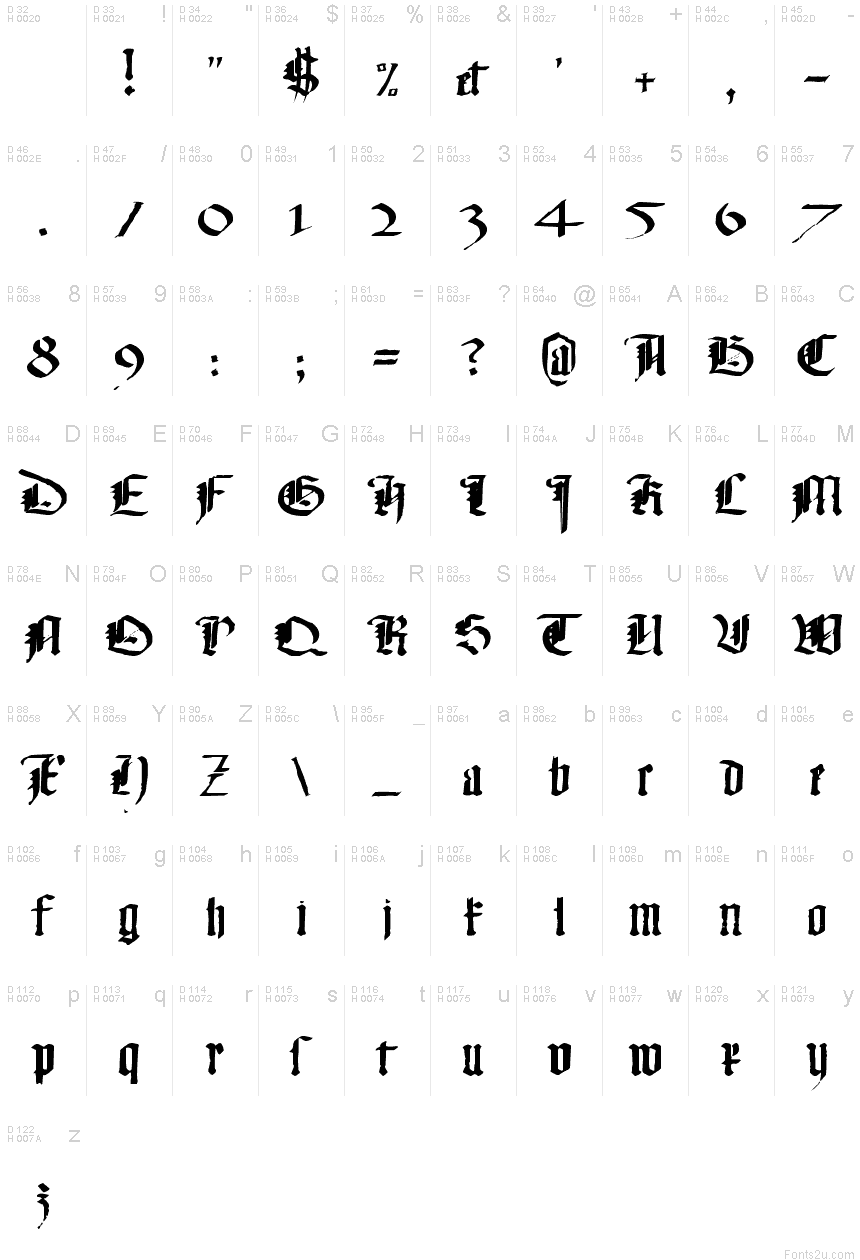
Monky Business od Anke Art to darmowy gotycki font średniowieczny o ostrych kształtach typu blackletter, rozdzielonych pionowych kreskach i spiczastych zakończeniach, które przywodzą na myśl pismo ręczne ze starych manuskryptów. Kanciaste formy i wyrazisty, „rzeźbiony” rytm sprawiają, że projekt ten mocno osadza się w stylistyce historycznych krojów akcydensowych. Monky Business świetnie sprawdzi się na okładkach książek fantasy, w logo heraldycznych, szyldach pubów, oprawach albumów czy tytułach plakatów, gdzie średniowieczny klimat robi całą robotę. Pasuje również do nagłówków zaproszeń i opakowań tematycznych, gdy potrzeba historycznego, ceremonialnego akcentu bez zbędnych zdobień.
Monky Business